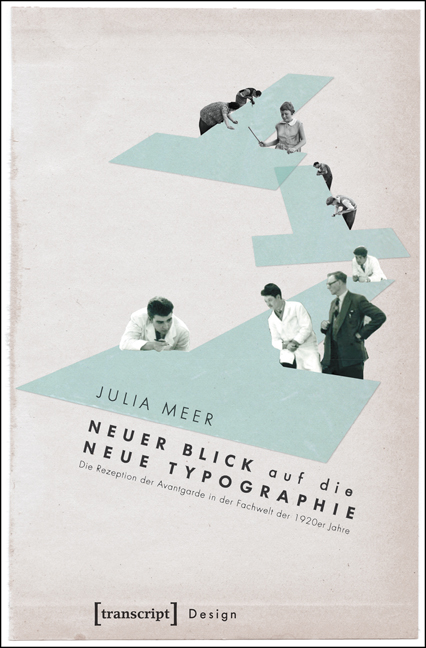
Neuer Blick auf die Neue Typographie - Julia Meer
Neuer Blick auf die Neue Typographie
Die Rezeption der Avantgarde in der Fachwelt der 1920er Jahre
Julia Meer stellt die bisherige Rezeptionsgeschichte des "Mythos Neue Typographie" in Frage und arbeitet zugleich die frühe Professionalisierung des Grafik-Designs auf. Durch eine systematische Auswertung von Fachzeitschriften der Jahre 1900-1933 zeigt sie, dass die Neue Typographie weder neu war noch aufgrund ihrer Modernität abgelehnt wurde. Vielmehr wurde sie früh von den Fachleuten gefördert und zu einem werbewirksamen Stil weiterentwickelt. Damit ging ein Prozess einher, in dem sich einige Protagonisten der Avantgarde von Künstlern zu Designern professionalisierten. Die Studie eröffnet neue Perspektiven auf die Wirkungsweise und Verbreitungsprinzipien von Design und das Selbstverständnis von Designern.
Julia Meer (Dr. phil.), Kommunikationsdesignerin, forscht im Exzellenz-Cluster »Bild Wissen Gestaltung« der Humboldt-Universität Berlin. Sie war von 2008-2014 Mitarbeiterin am Institut für Kunst- und Designwissenschaft der Bergischen Universität Wuppertal und gestaltete dort Ausstellungen und Kataloge (u.a. zu Max Burchartz und zu Mies van der Rohes »Barcelona Chair«). 2012 gab sie den Band »Women in Graphic Design 1890-2012« mit heraus. Neben der wissenschaftlichen Arbeit ist sie selbstständige Gestalterin und Herausgeberin des Magazins ff.